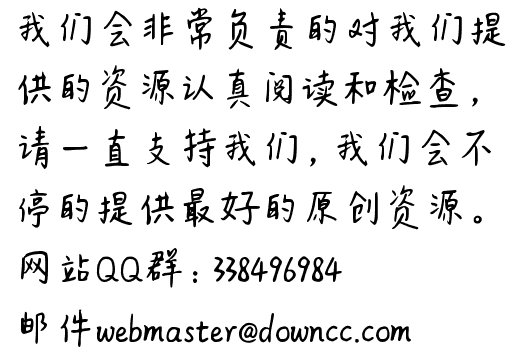
思雨胡瘦瘦體是思雨字體庫中的一款十分可愛的卡通字體,以瘦為魂,每個漢字都顯得十分小巧,圓潤的結(jié)構(gòu)讓其顯得憨態(tài)可掬,不信就來綠色資源網(wǎng)看看吧!
思雨胡瘦瘦體是根據(jù)胡瘦瘦同學(xué)書寫的硬筆字制作完成,該字體筆畫圓潤,結(jié)構(gòu)松散明快,給人一種笨笨的感覺,喜歡這種風(fēng)格的童鞋不要錯過哦!
思雨胡瘦瘦ttf字體有著簡約樸實(shí)的硬筆書法字體風(fēng)格,兼具手寫字體和pop字體的亮點(diǎn),風(fēng)格獨(dú)特藝術(shù)效果極佳,給你的海報設(shè)計、包裝設(shè)計、廣告設(shè)計、平面設(shè)計等帶來不錯的體驗!